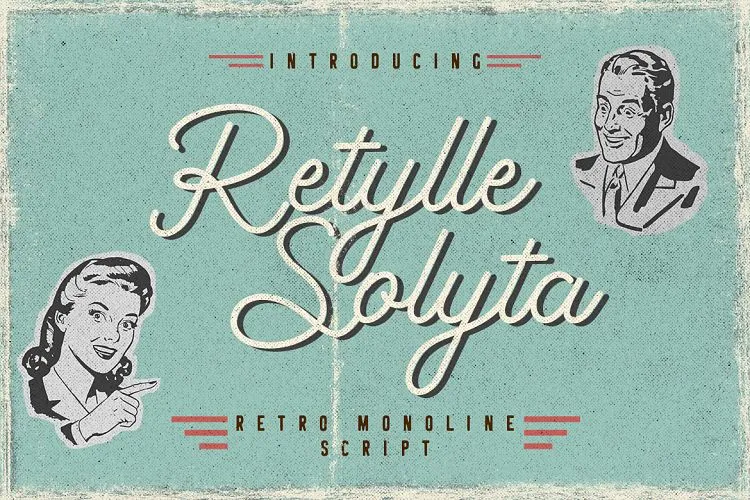
Aqui está uma descrição envolvente e natural para a página de download da font ‘Retylle Solyta Script Font’: Repleta de nostalgia, Retylle Solyta Script é uma fonte retro que carrega consigo um ar vintage encantador. Ideal para qualquer projeto gráfico que busque um toque de simplicidade e elegância clássica, esta fonte monoline se destaca como o complemento perfeito para criações de marca, logomarcas, cartões de wedding design, postagens no Instagram, anúncios e embalagens. A sua textura única é uma grata surpresa para os profissionais do mundo da design, oferecendo-lhes flexibilidade para adaptá-la a uma vasta gama de projetos, desde criações de produto até ao desenvolvimento de etiquetas e materiais publicitários. Com Retylle Solyta Script, as designers e criativos brasileiros podem elevar qualquer projeto à próxima dimensão, com os seus traços suaves e elegantes garantindo um toque final personalizado que captura o instante perfeito. Não importa se está a trabalhar em uma criação de marca inovadora ou na elaboração de um cartaz para um casamento, esta fonte tem tudo o que precisa para complementar a sua paleta criativa e manter-se atual, enquanto faz seu trabalho de fundo sem tirar o foco do projeto.